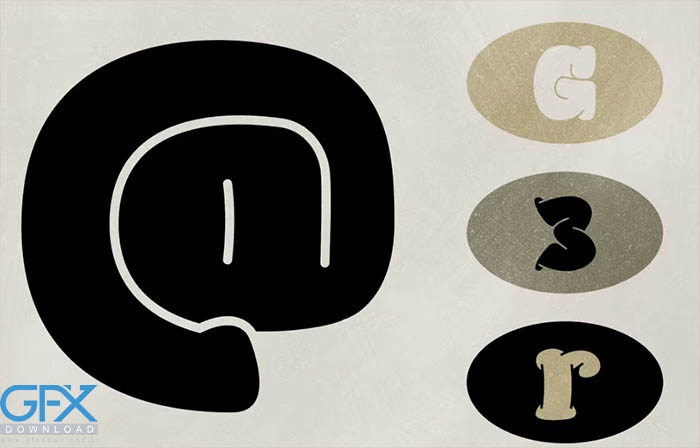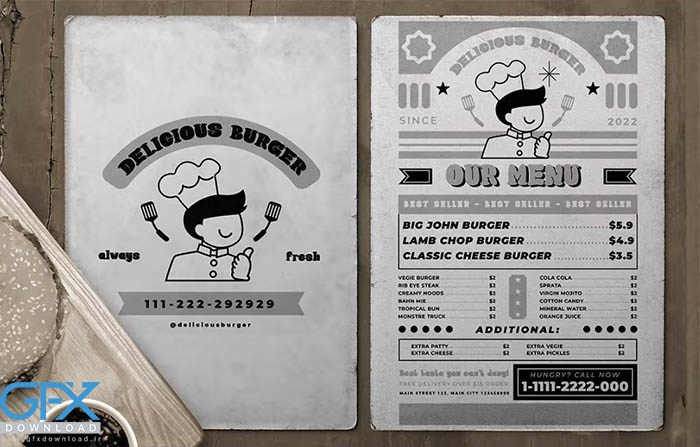
دانلود فونت قدیمی Goof Ball
دانلود فونت انگلیسی قدیمی Goof Ball
این فونت جذاب برای پروژه‌های سرگرم‌کننده به سبک قدیمی مناسب است. دانلود فونت قدیمی Goof Ball عالی مناسب برای بازار کتاب های مصور با سیستم عامل، بازی های آنلاین، پوسترهای رویدادهای قدیمی، فونت وسایل مدرسه، پوسترها، عنوان فیلم ها، جلدهای یوتیوب، تصاویر کوچک یوتیوب، جلد صفحه رسانه های اجتماعی و غیره...